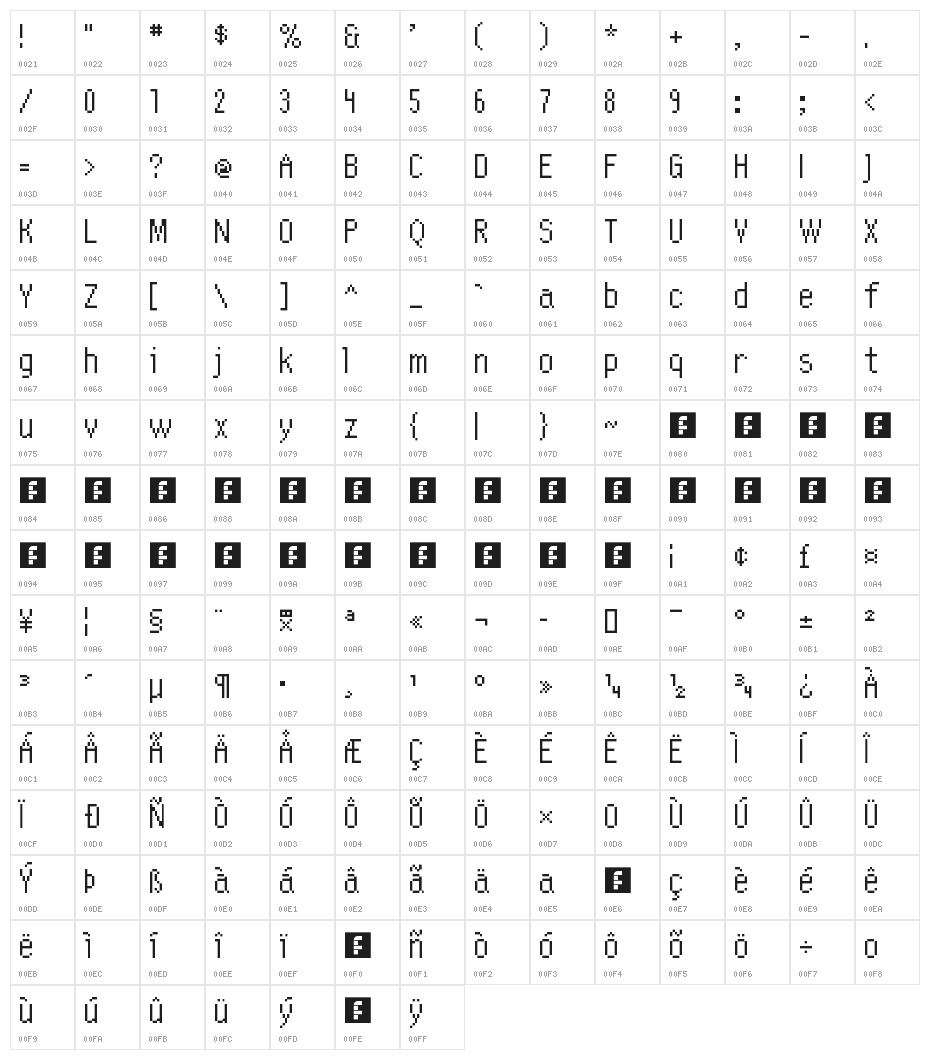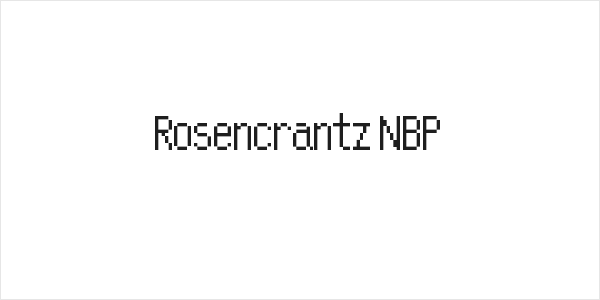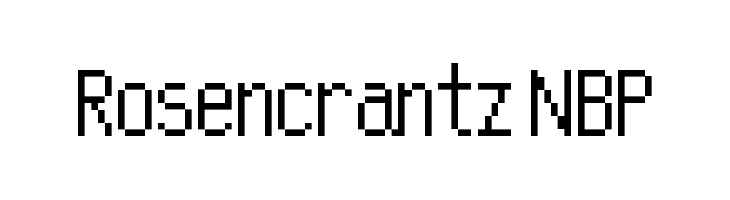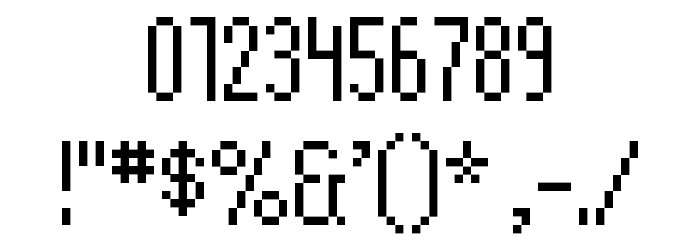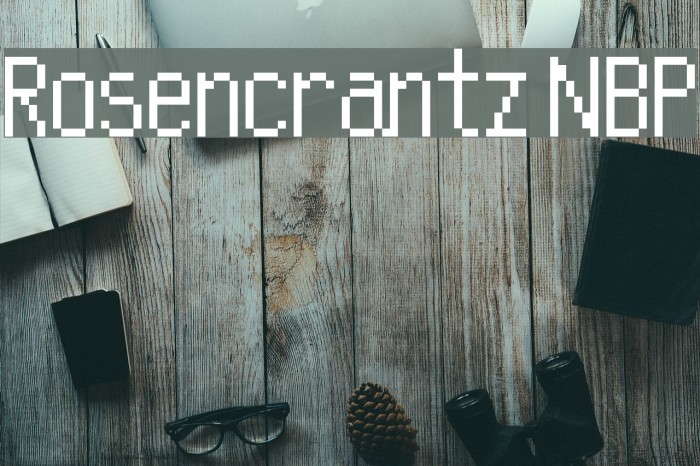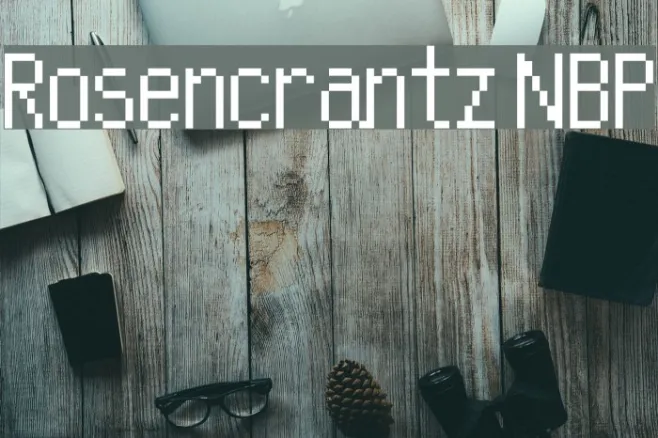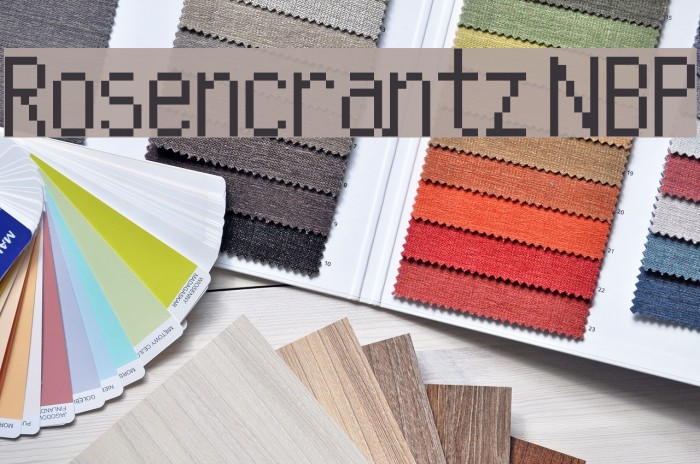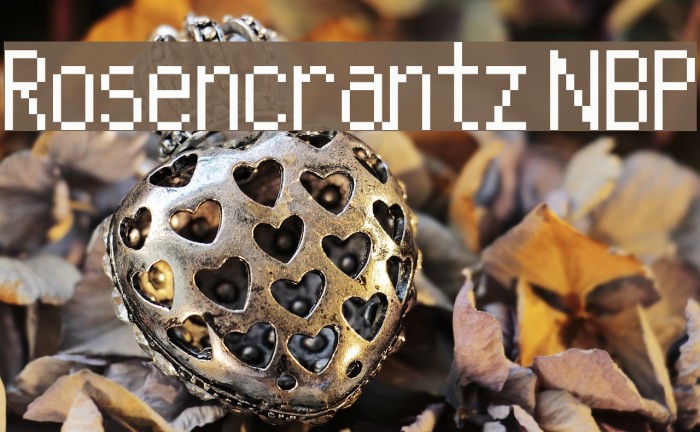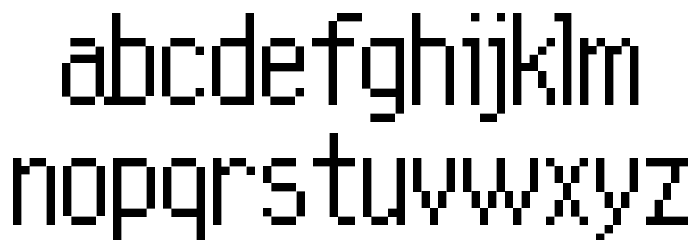
Rosencrantz NBP Font
✎ Pixel
| Style général | Retro, Digital |
| Cas d'utilisation | Headlines, Logos, Digital displays |
| Projets proposés | Ideal for retro video game designs, digital art projects, tech-themed posters, and any creative work that seeks a nostalgic or digital feel. |